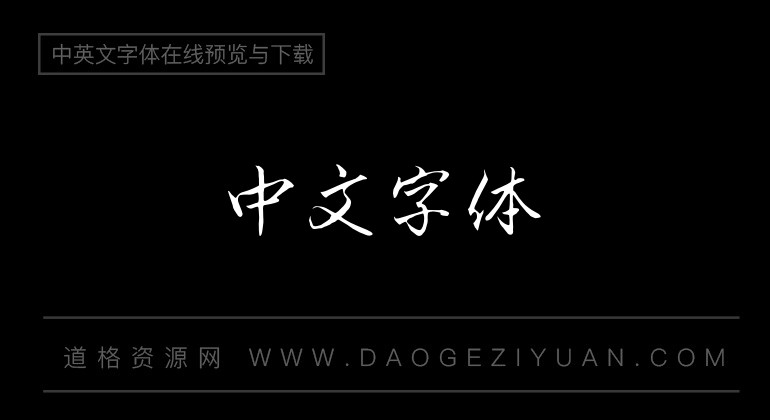
A-OTF 角新行書 Std L
A-OTF 角新行書 Std L 字体是一款由日本Adobe公司开发的日文行書字体,它是一款基于Adobe OpenType Font Format(A-OTF)技术的行書字体,它拥有较高的可读性和精细的排版,可以满足日文行書的需求。A-OTF 角新行書 Std L 字体拥有非常丰富的字符集,其中包括了日文汉字、标点符号、数字、英文字母等,可以满足不同类型的文章的书写需求。此外,A-OTF 角新行書 Std L 字体还支持日文多音节和双元音,可以更好地表现日文的精细文字特征。
A-OTF 角新行書 Std L是一款非常不错的手写艺术字体,具有很好的视觉感,适合于文化类的宣传设计、商业类品牌的广告和产品包装设计以及个性化文字排版等较多场景。